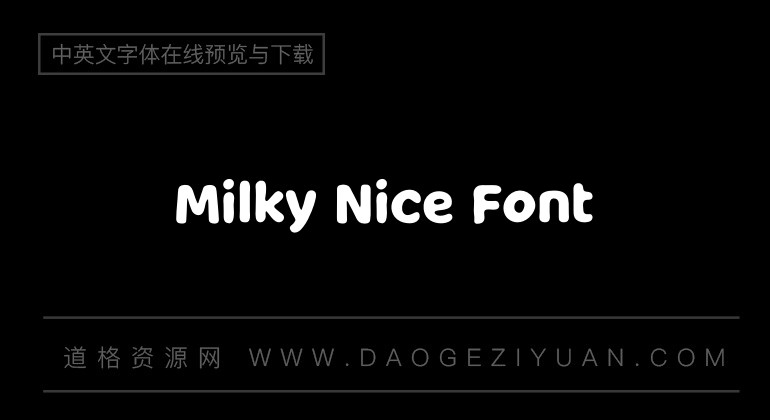
Milky Nice Font 是一种现代、流畅的字体,拥有圆滑的线条和简洁的外观。它由设计师图灵制造厂(Turing Machine)设计,于2018年发布。这种字体的特点是: 1. 清晰易读:Milky Nice Font 的线条清晰,字母之间的空间适中,非常容易阅读。 2. 圆滑流畅:Milky Nice Font 的每个字母都采用了圆润的线条,让整个字体看起来非常流畅。 3. 简洁现代:Milky Nice Font 的设计非常简洁,没有太多花哨的装饰,给人一种现代感。 4. 多语言支持:这种字体支持多种语言,包括英语、西班牙语、法语和德语等。 这些特点使得 Milky Nice Font 在许多设计中得到了广泛的应用,尤其是在品牌标识、海报设计和印刷品设计等方面。内容介绍
Milky Nice Font是一款非常不错的手写艺术字体,具有很好的视觉感,适合于文化类的宣传设计、商业类品牌的广告和产品包装设计以及个性化文字排版等较多场景。